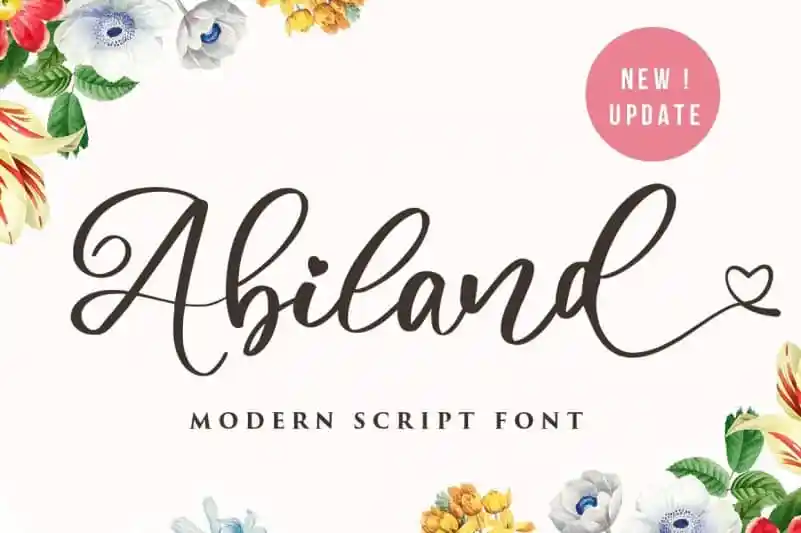
Abiland Calligraphy Font – Download Grátis
A Abiland Calligraphy Font é uma elegante tipografia feita à mão que desliza suavemente entre sua página. Este tipo de escrita delicada e bem equilibrado atende a um grande número de projetos, desde rótulos para produtos gourmet até design gráfico minimalista. A fonte foi criada pela Vultype Co., inspirada em fóruns de escrever em letras contemporâneas com ligaduras e estilos alternativos para adicionar uma aparência única e floridinha aos seus projetos. Ela não apenas se ajusta a diversos ambientes design, mas também adiciona um toque único e charmoso que certamente tornará qualquer projeto mais especial. Ideal tanto para designers de produtos como para aqueles trabalhando em projetos digitais ou impressos, a Abiland Calligraphy Font é perfeita para quem deseja dar ao seu design um visual mais elaborado e encantador.